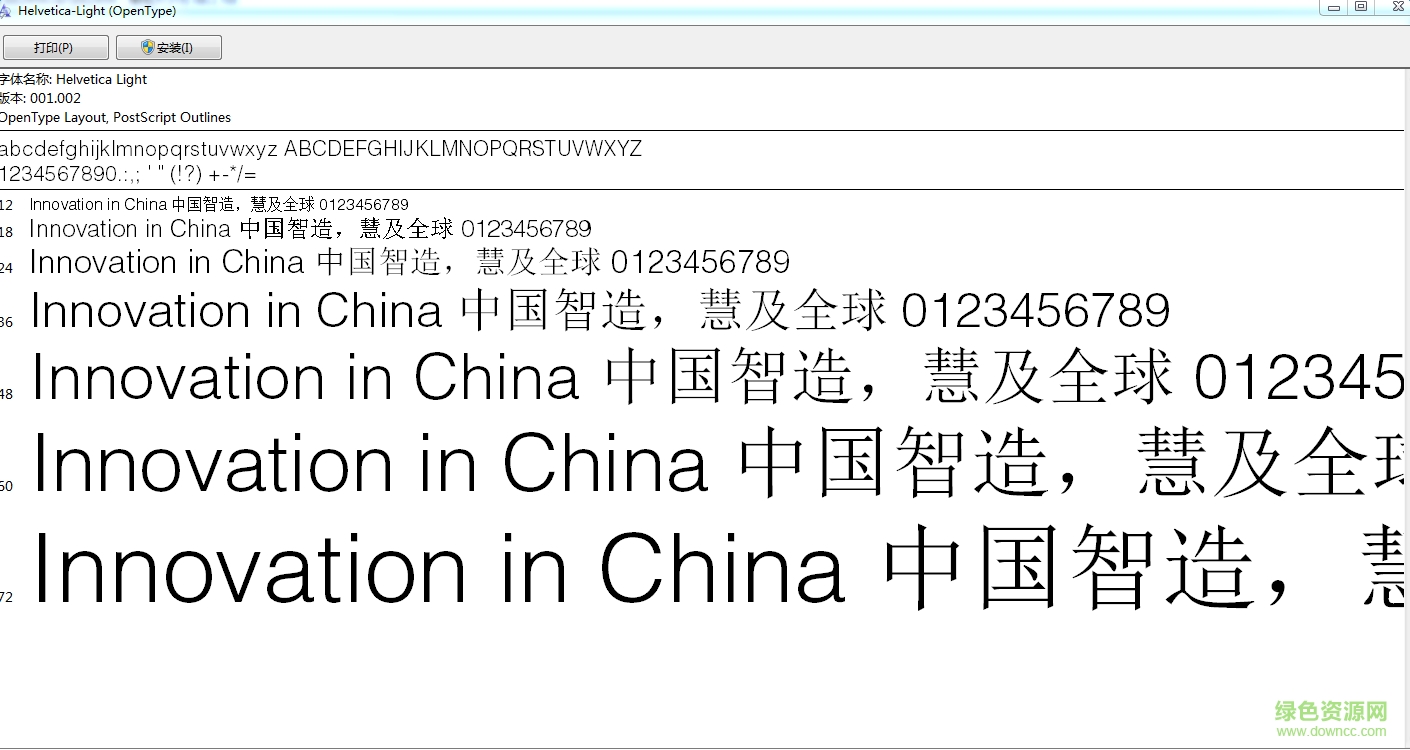
helvetica light oblique字體是一款十分優(yōu)雅的英文字體,筆觸纖細(xì)又不失力道,非常易于閱讀,適用的領(lǐng)域非常廣泛,喜歡的朋友快來綠色資源網(wǎng)下載吧!
helvetica light字體沒有襯線裝飾,筆跡全部一樣粗細(xì),清晰度較高,可用作各類文章正文字體!